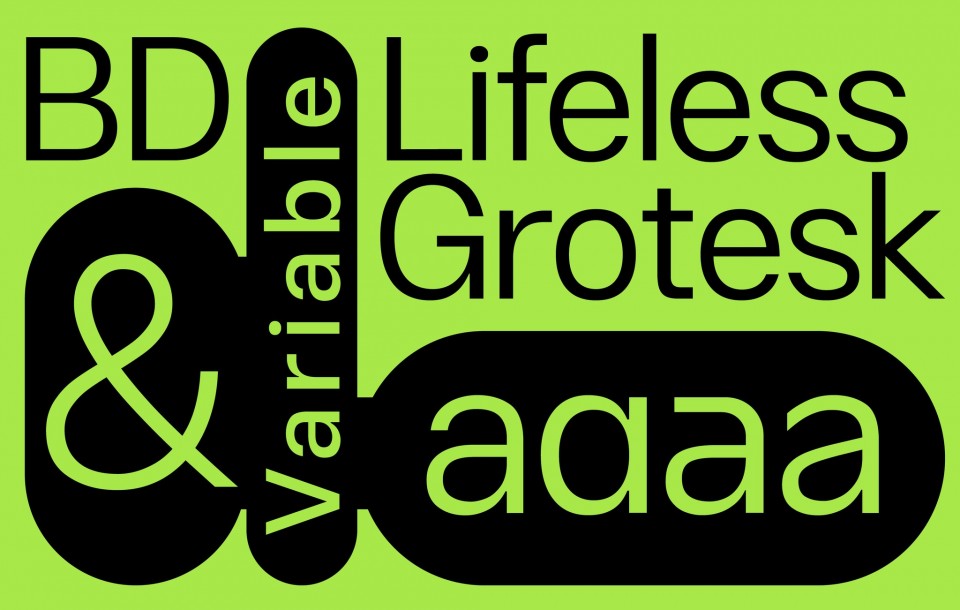
Tải Font tiếng việt BD Lifeless Grotesk Miễn Phí Cho Thiết Kế Hiện Đại
Font tiếng việt BD Lifeless Grotesk là một trong những bộ phông chữ thuộc trường phái Neo-Grotesque được ưa chuộng nhất hiện nay bởi sự tối giản và tính ứng dụng cao. Nếu bạn đang tìm kiếm một Font Chữ có đường nét gọn gàng, mang hơi thở của phong cách thiết kế Thụy Sĩ cổ điển nhưng vẫn rất hiện đại thì đây là lựa chọn hàng đầu. Bộ font này được tối ưu hóa khả năng hiển thị trên các nền tảng kỹ thuật số giúp người dùng dễ dàng truyền tải nội dung một cách trực quan và chuyên nghiệp nhất trong mọi dự án đồ họa hay trình bày văn bản.
Đặc điểm nổi bật của Font tiếng việt BD Lifeless Grotesk
Lý do khiến Font tiếng việt BD Lifeless Grotesk trở nên phổ biến chính là cấu trúc hình học chuẩn xác và độ tương phản thấp. Điều này giúp các ký tự giữ được sự rõ nét ngay cả khi hiển thị ở kích thước nhỏ nhất.
Tính ứng dụng trong giáo dục và thiết kế
Trong môi trường học đường, việc sử dụng các font chữ không chân như BD Lifeless Grotesk giúp học sinh dễ dàng tiếp nhận thông tin từ các slide bài giảng hoặc tài liệu tham khảo. Font đã được việt hóa đầy đủ các dấu câu chuẩn giúp người dùng không còn lo lắng về lỗi hiển thị khi soạn thảo tiếng Việt.